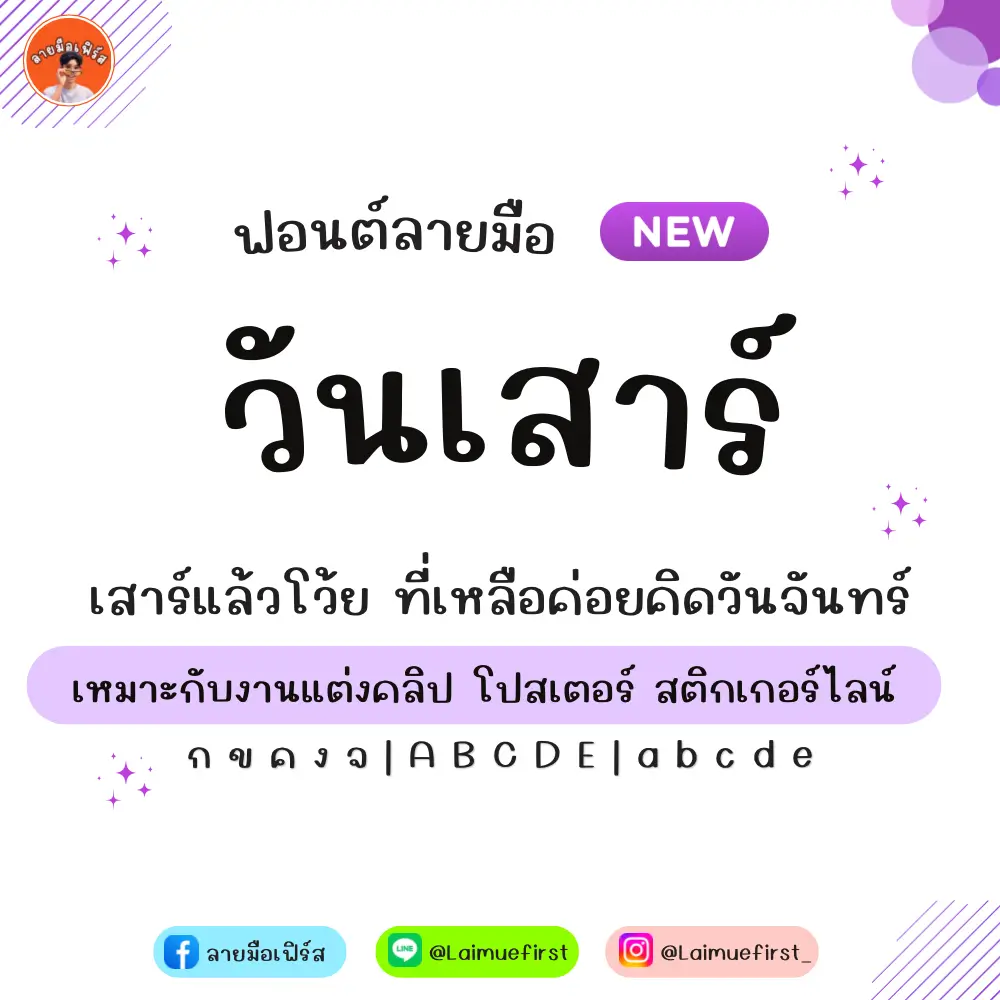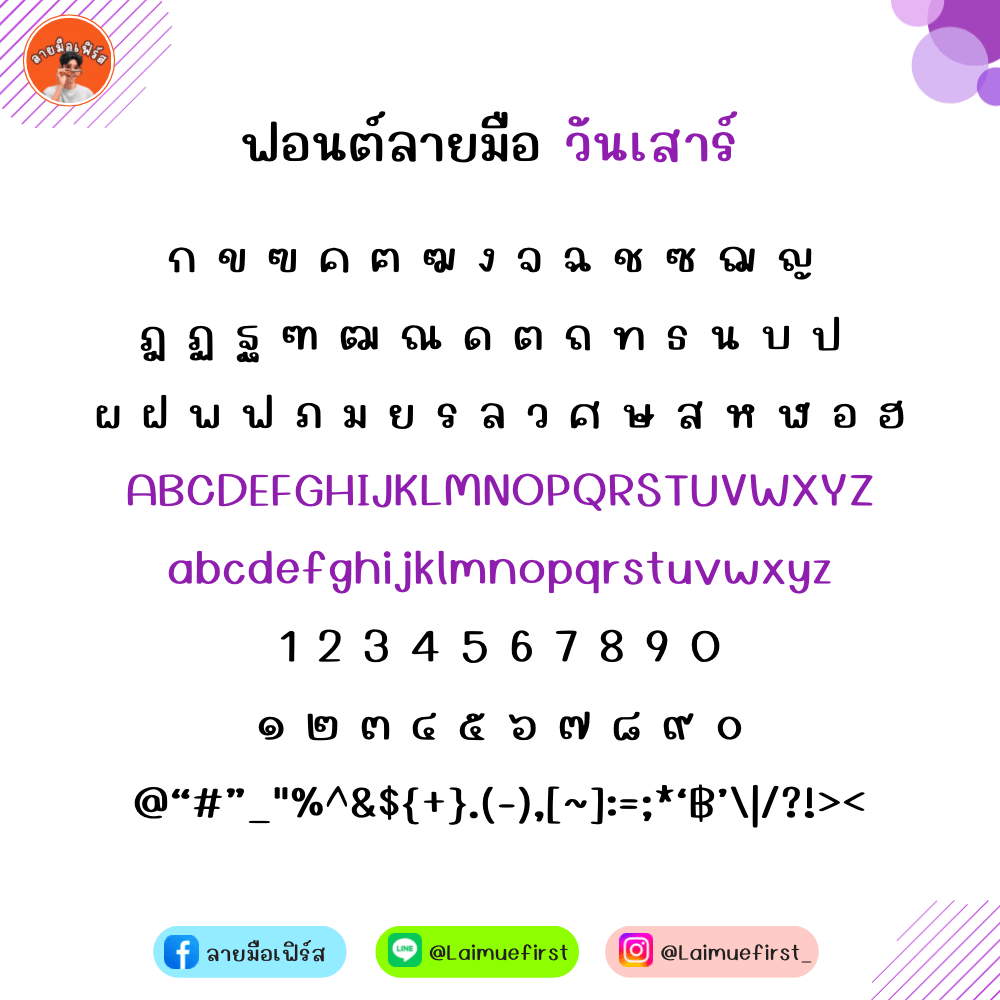
ฟอนต์ลายมือ วันเสาร์ (LMF Wansao) – แจกฟรีสำหรับทดลองใช้งานแบบส่วนตัว เวอร์ชันทดลอง (Demo)
- จะได้รับฟอนต์ 3 ขนาด (ปกติ/หนา/บาง)
- ตัวหนังสือปกติ ไม่มีตัวโปร่งปน
วันเสาร์ (LMF Wansao)